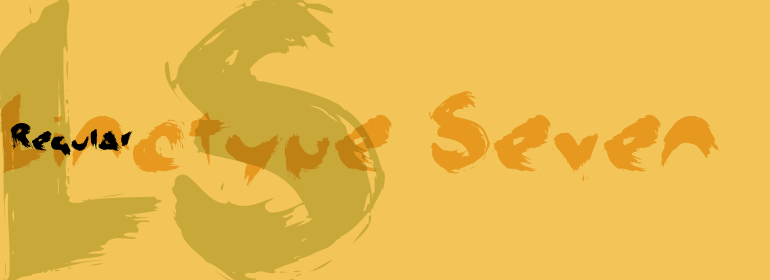
Linotype Seven™
Linotype Seven包含在TakeType字体库中,它是从1994年和1997年Linotype举办的的International Digital Type Design Contest的参赛作品中选出的。这款获奖的字体由德国艺术家Christian Vornehm设计。该字体看起来好像是用宽大的笔刷草草绘制而成,好像抄写员很着急。Linotype Seven充满活力和自发性。它专门用于较大字号的短标题。
Linotype Seven is part of the Take Type Library, chosen from the contestants of Linotype's International Digital Type Design Contests of 1994 and 1997. This prize-winning font was designed by the German artist Christian Vornehm. The font looks as though hastily drawn with a wide, bristly brush, as though the scribe was in a hurry. Linotype Seven is loaded with energy and spontaneity. It is intended exclusively for short headlines in larger point sizes.